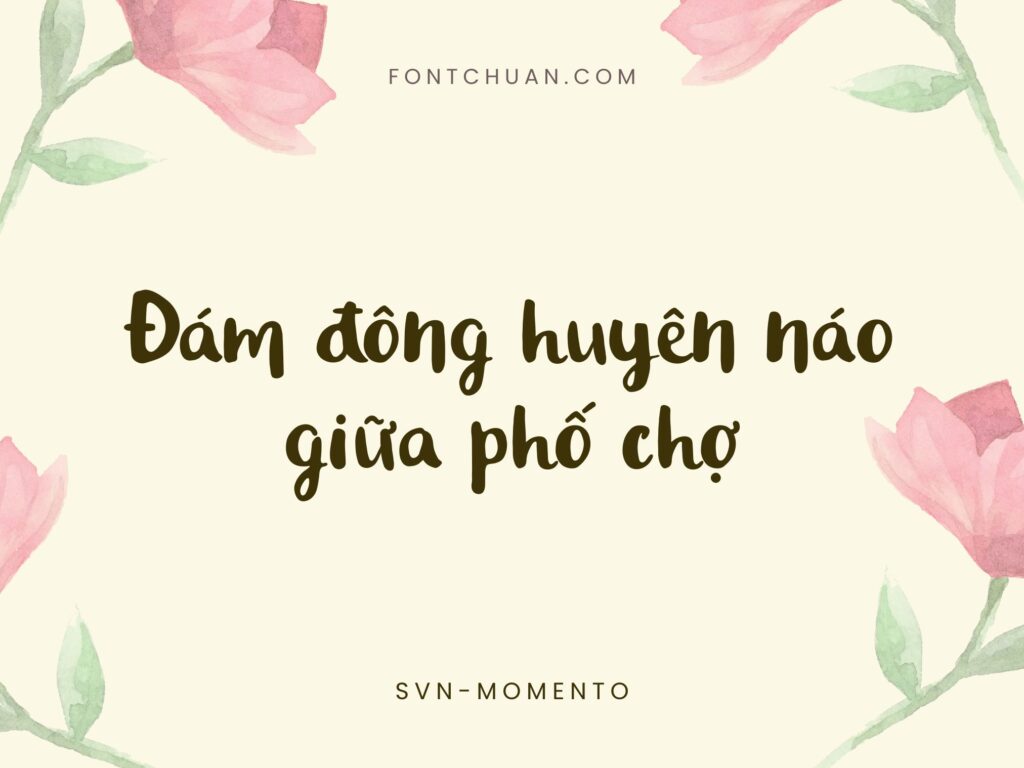
Font SVN Momento là phiên bản Việt hóa của kiểu chữ Momento, được thực hiện bởi STYLEno.1 Fonts. Momento là một kiểu chữ viết tay với nét đậm và mềm mại, mang lại cảm giác thân thiện và tự nhiên. Font này bao gồm đầy đủ các ký tự chữ hoa, chữ thường, chữ số và dấu câu, hỗ trợ đa ngôn ngữ. Momento phù hợp cho nhiều mục đích sử dụng khác nhau như thiết kế thiệp mời, logo, tiêu đề, bao bì sản phẩm và các ấn phẩm truyền thông.
SVN Momento lý tưởng cho các dự án thiết kế yêu cầu sự mềm mại và thân thiện, như thiết kế thiệp mời, logo thương hiệu và các ấn phẩm truyền thông. Font này cũng có thể được ứng dụng như một Font chữ ẩm thực, giúp các nhà hàng, quán ăn và thương hiệu thực phẩm tạo ra sự gần gũi, tinh tế và hấp dẫn trên menu, bao bì hoặc các ấn phẩm quảng cáo. Ngoài ra, SVN Momento vẫn phù hợp cho các ngành thiệp cưới, giáo dục, cũng như các sự kiện như Valentine, Sinh nhật, Tết và các lễ hội khác.